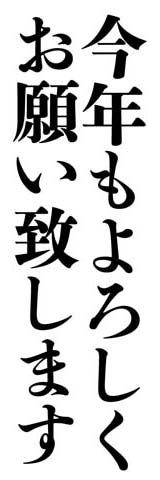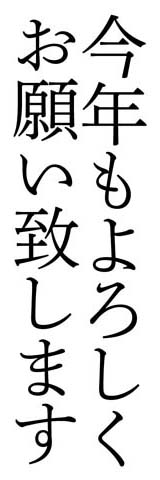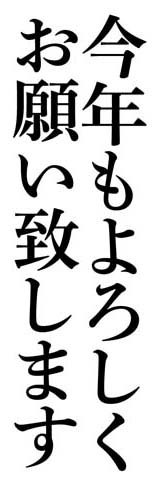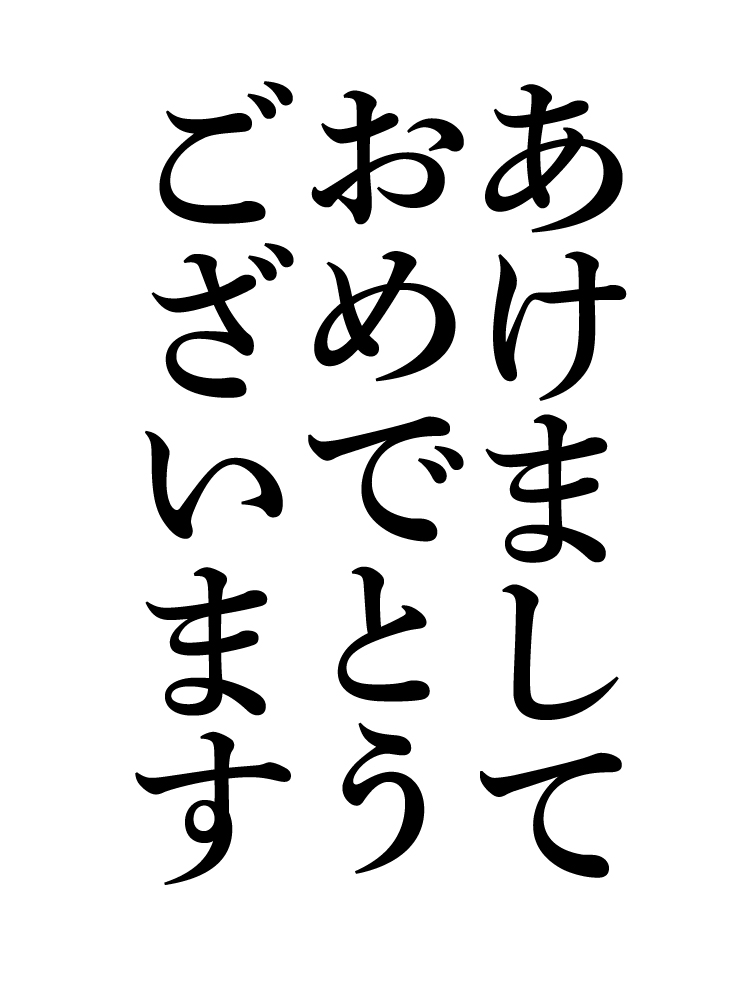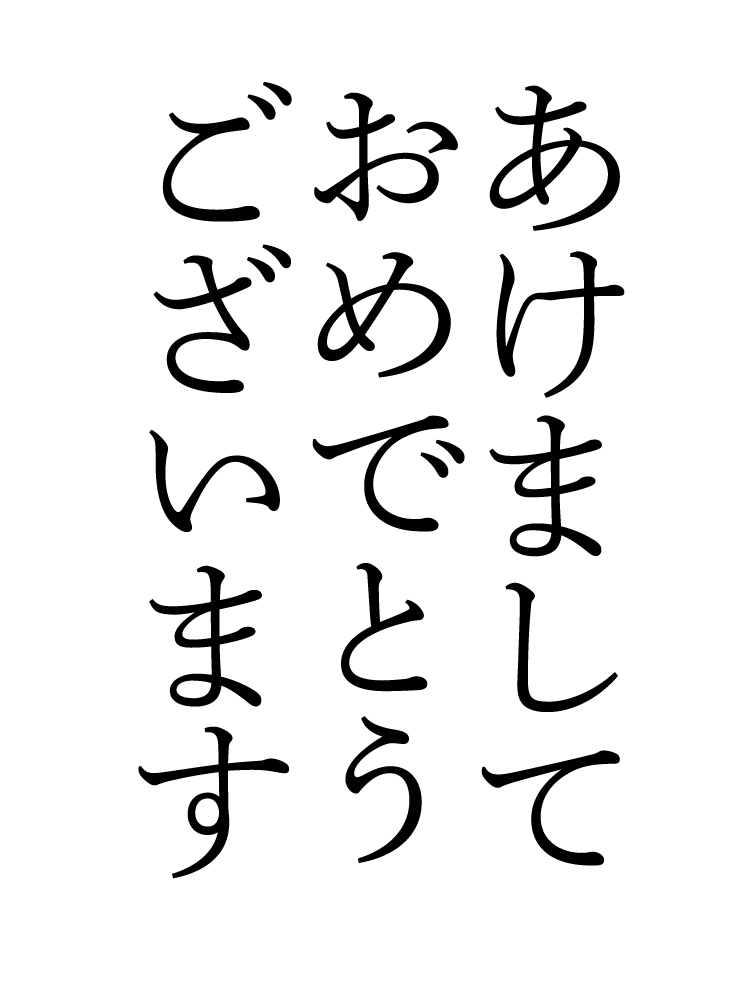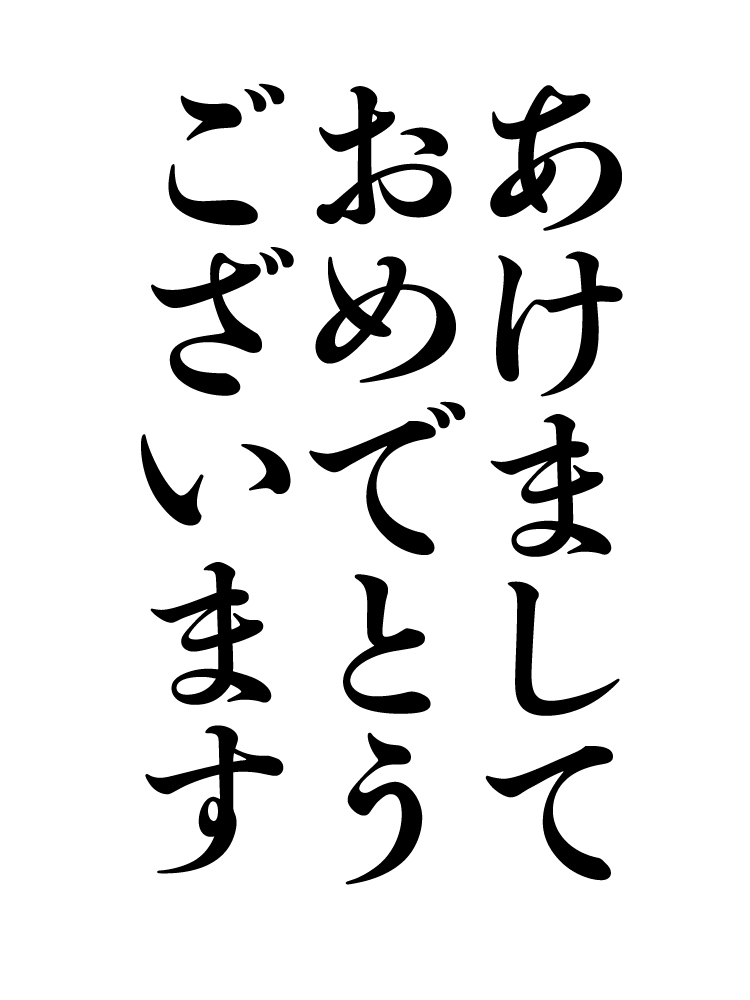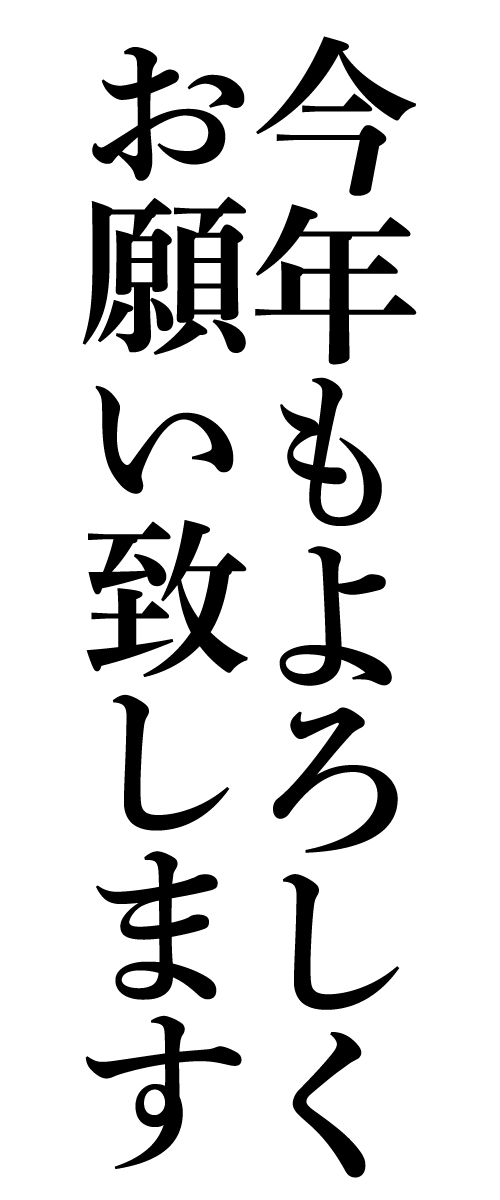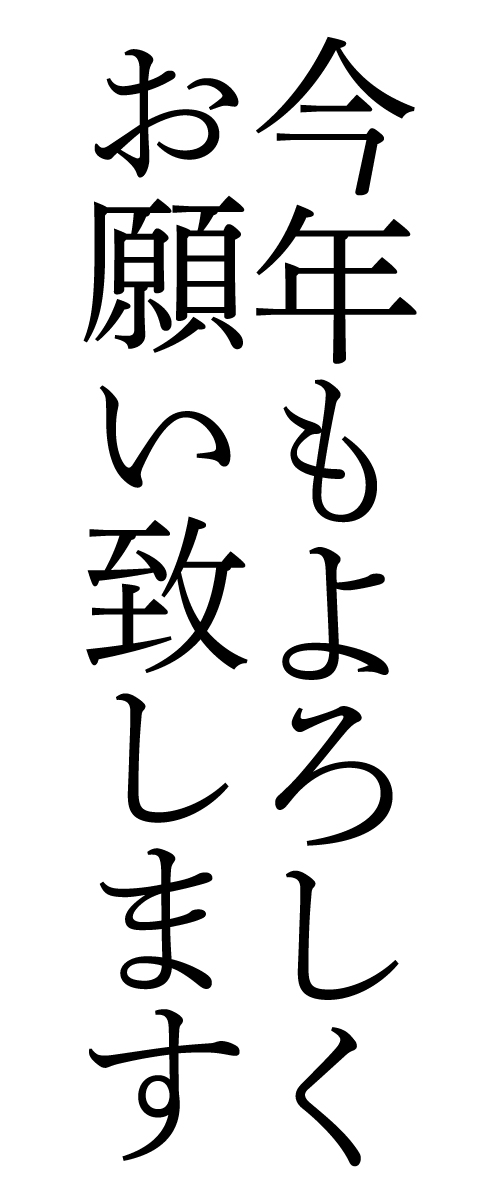
第23回 2007年も大正3年『活版見本帖 Type Specimens』から年賀状を作ろう!
連休も明けてしまい、テレビで年賀状のCMが流れるたびに焦る皆様へ、今年も秀英体で年賀状はいかがでしょうか。
今回の秀英体のコネタは、一年間のご愛顧に感謝いたしまして、秀英舎・大日本印刷が誇る最大規模の見本帳、大正3年版『活版見本帖 Type Specimens』から、来年の干支であるねずみや冬・新春らしい柄などをピックアップいたしました。
まだ年賀状を作っていない方、一昨年の「第14回 大正3年『活版見本帖 Type Specimens』から年賀状を作ろう!」や昨年の「第21回 2006年も大正3年『活版見本帖 Type Specimens』から年賀状を作ろう!」と併せ、ぜひご活用ください!
2008の干支、ねずみ集合!
来年の干支はねずみ。ちなみに十干十二支では戊子となります。ねずみは子孫繁栄の縁起ものでもあります。大黒天のおつかいとしてもおなじみですね。
ねずみは昨年のいのししよりはやはり見本帳に掲載されていました。
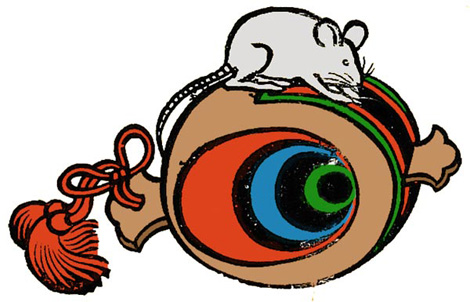
小槌にのったねずみ
ちょっと小さめの画像なので、アクセントとしてどうぞ。
しっぽが枠になっています。
ぶどうとねずみ
こちらは子歳と書かれた凧です。白い部分にメッセージなどをどうぞ。
羽子板、鞠、熨斗とねずみ。おめでたいもの尽くしです。
ねずみもお正月は書初めです。
大黒様からえびす様への年賀状?
ねずみ以外のおめでた柄などは
にもたくさん掲載されていますので、どうぞご覧下さい。
「あけましておめでとうございます」を秀英体で!
絵が決まったら、ご挨拶のテキストです。
見本帳に掲載されていた見出し用の数字で「2008」です。インクのかすれた部分が、味わいがあります。
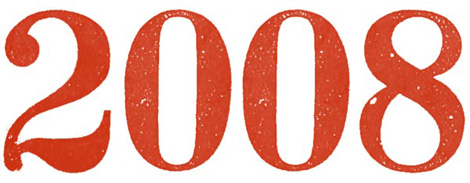
どーんと主役で使ってください
そして絵に添えることばをぜひ秀英体で!
改刻中の秀英初号明朝ならびに秀英細明朝・太明朝でお正月っぽい言葉を並べてみましょう(中明朝はまだ進めている最中ですので、残念ながらご紹介できません)。
来年も、秀英体の取組みをご紹介してまいります。変わらないようで変わっていく秀英体を、2008年もよろしくお願い致します。